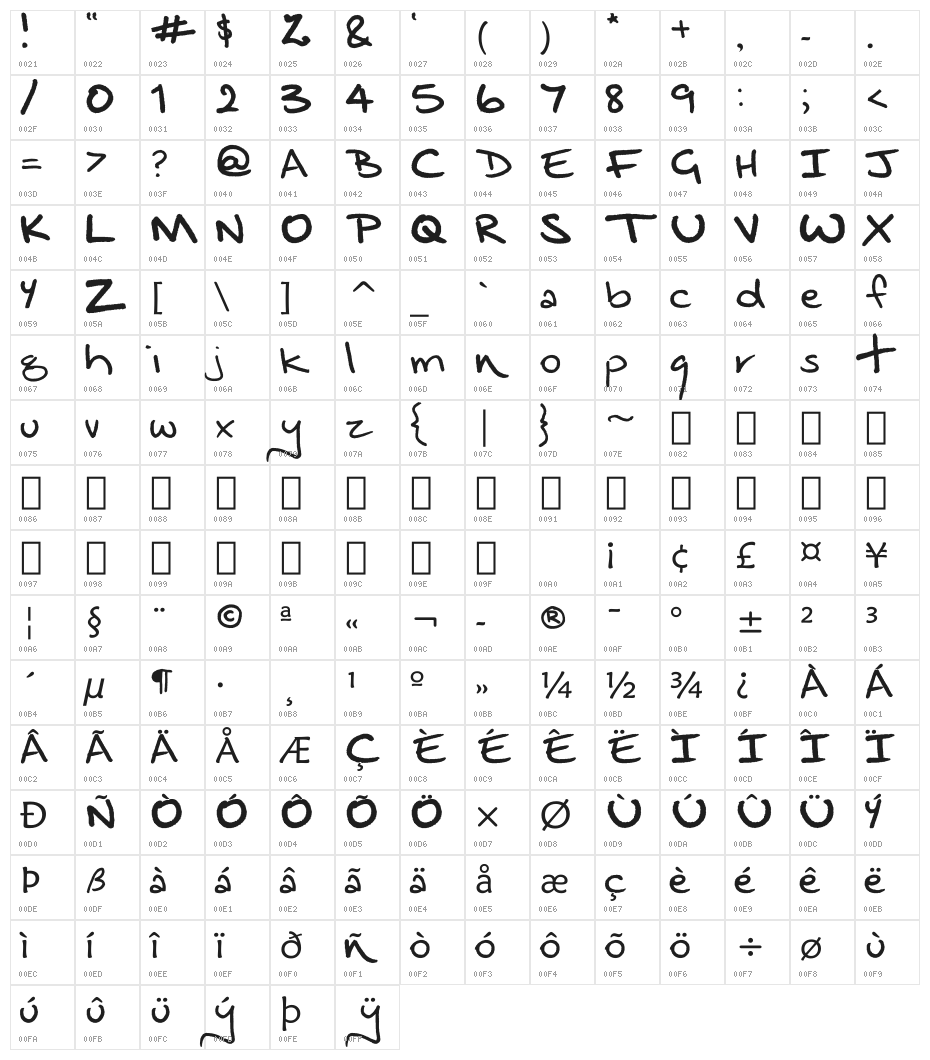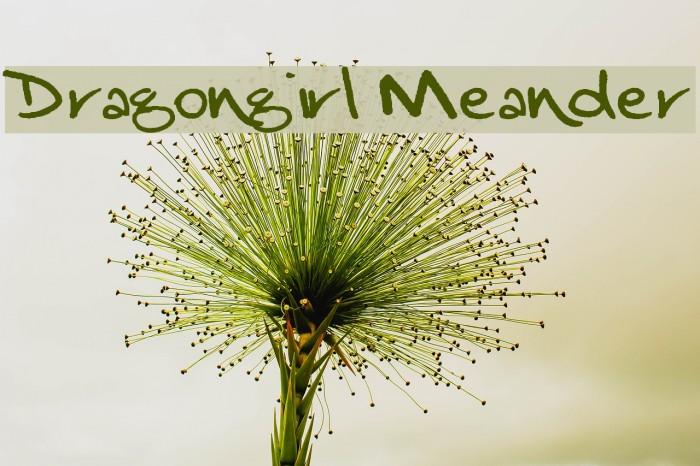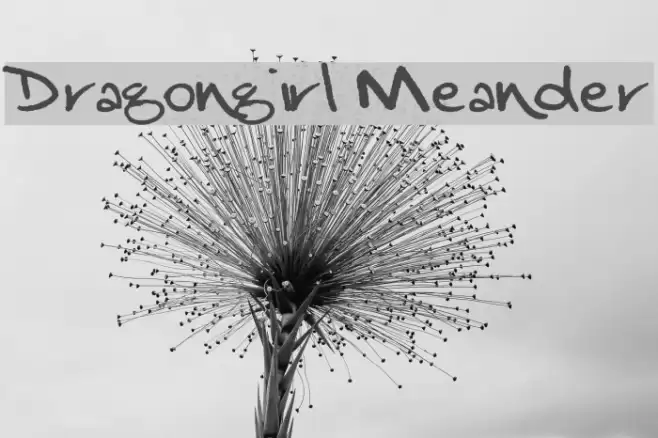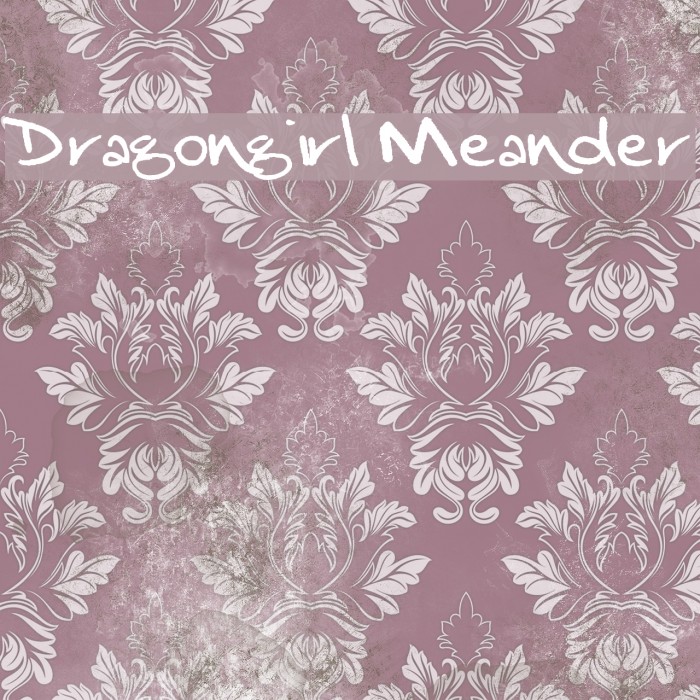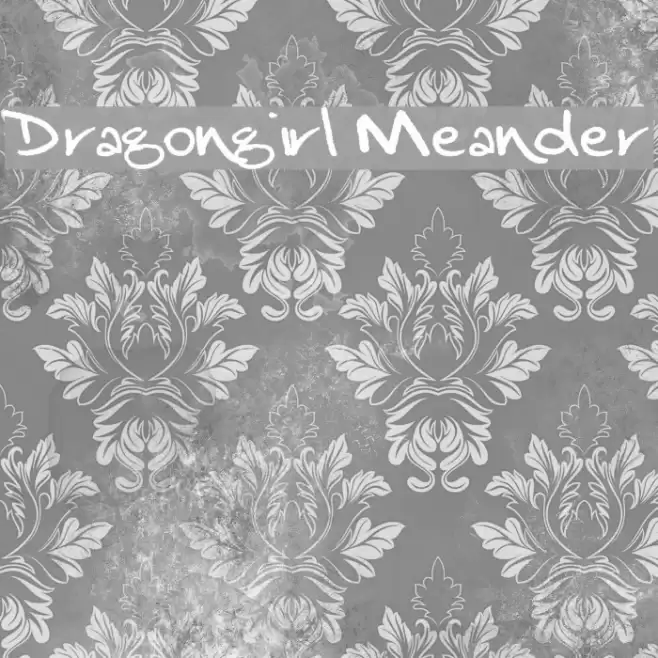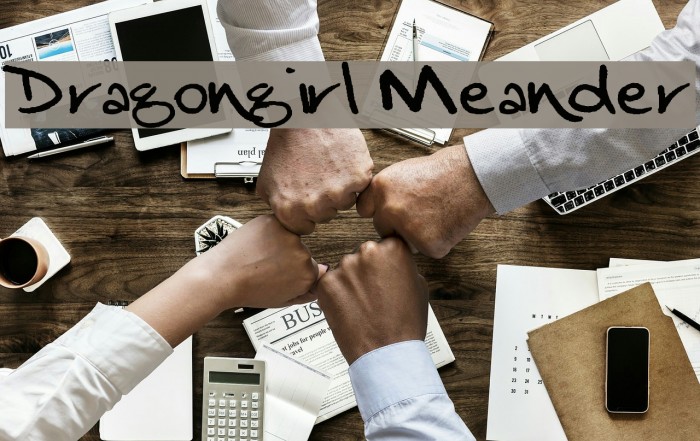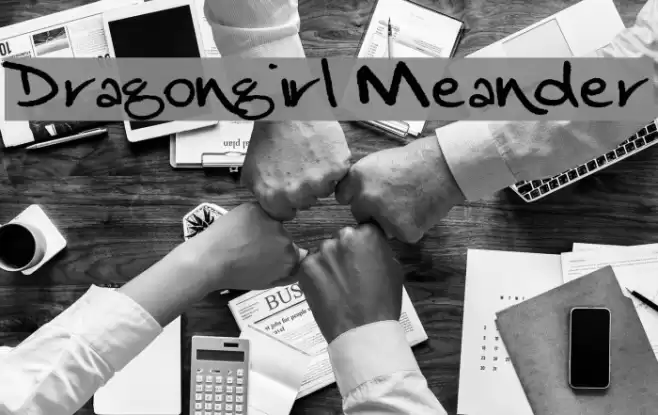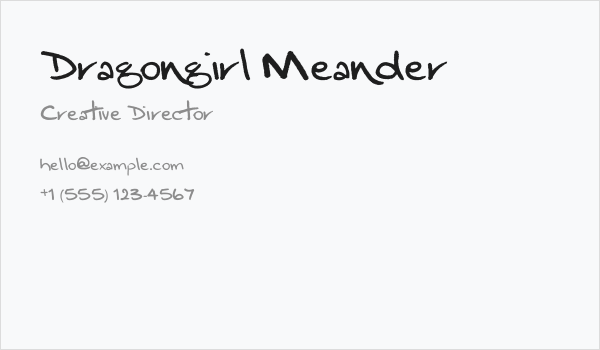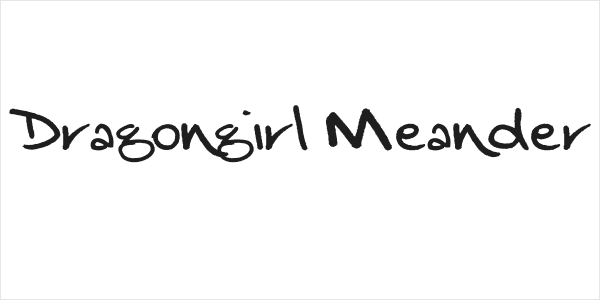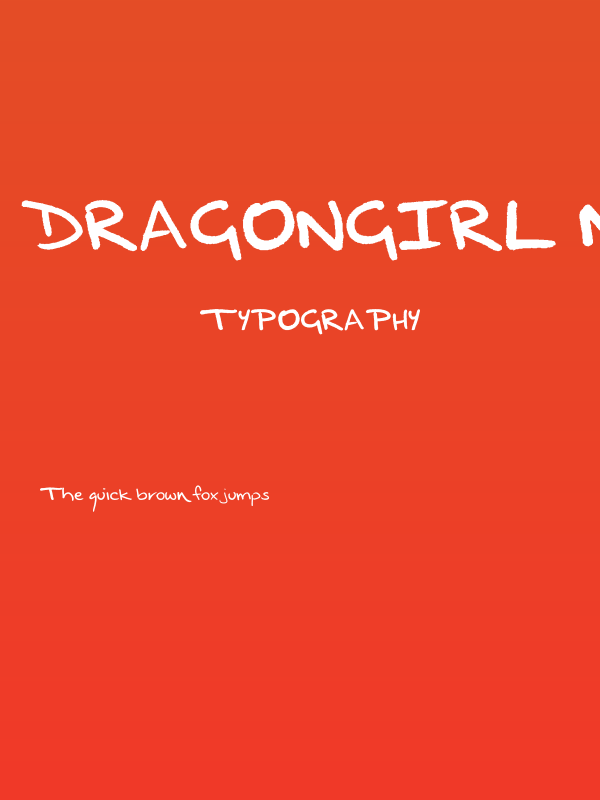
Dragongirl Meander Font
| Nombre | Dragongirl Meander |
| Peso | Boggled |
| Estilo general | Casual, Playful |
| Caso de uso | Headlines, Informal text, Creative projects |
| Proyectos propuestos | Ideal for greeting cards, personal invitations, children's books, and creative branding projects. |